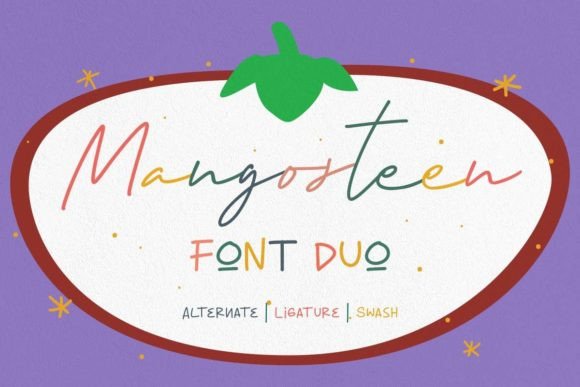
Mangosteen
Mangosteen Font Duo: A Doçura que Transforma Seu Design
Se você está em busca de uma tipografia que una beleza e versatilidade, a Mangosteen Font Duo chega como a escolha perfeita. Inspirada na fruta exótica mangostão, essa fonte manuscrita traz consigo uma aura suave, acessível e extremamente cativante, ideal para quem deseja dar um toque humano e acolhedor a projetos criativos.
- Estilo manuscrito duplo: duas variações que permitem combinar títulos e corpos de texto com harmonia.
- Leitura fluida: traços leves e bem espaçados que garantem legibilidade mesmo em tamanhos menores.
- Versatilidade de uso: perfeita para cartões de felicitação, ilustrações, citações inspiradoras, branding, capas de livros, livros infantis, embalagens e muito mais.
Por que escolher Mangosteen Font Duo?
Assim como o mangostão é conhecido como a “rainha das frutas” por seu sabor doce e refrescante, a Mangosteen Font Duo se destaca no universo tipográfico ao oferecer:
- Atmosfera amigável: transmite calor e proximidade, ideal para comunicação visual que deseja criar conexão emocional.
- Flexibilidade criativa: permite misturar as duas variações – regular e cursiva – para criar hierarquias visuais dinâmicas.
- Impacto visual: destaca suas mensagens em projetos de branding e embalagens, ajudando a diferenciar sua marca da concorrência.
Aplicações Ideais
- Cartões de felicitação e convites personalizados
- Ilustrações e quotes para redes sociais
- Identidade visual de marcas artesanais e eco‑friendly
- Capa de livros infantis e materiais educacionais
- Design de embalagens de produtos gourmet e naturais
Se você quer dar ao seu projeto um toque doce, suave e cativante, a Mangosteen Font Duo é a escolha certa. Seu estilo manuscrito duplo oferece a combinação perfeita entre elegância casual e legibilidade, fazendo com que cada palavra pareça escrita à mão com carinho. Não perca tempo – experimente agora e descubra como essa fonte pode transformar a percepção da sua marca.